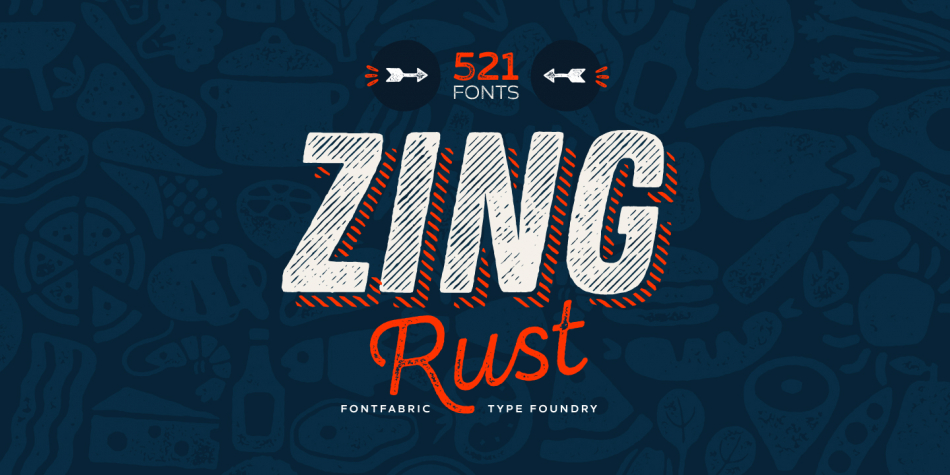
A fonte Zing Rust Font Family é uma família extensa de tipografia projetada com cuidado por Hamilton, disponível na categoria de Fontes para todos os seus projetos design. Especialmente indicada para criadores que buscam uma paleta vibrante e dinâmica, essa família oferece quatro subfamilias: Zing Rust, Zing Script Rust, Zing Sans Rust e Zing Goodies Rust. Zing Rust é o protagonista desta família, trazendo a essência vital e fresca dos ideais e das criações arrojadas de seus criadores. Zing Script Rust e Zing Rust incluem recursos OpenType com alternativas contextualizadas para oferecer uma ampla gama de personalização. A fonte Zing Rust é um ícone da família, destacando-se pelo seu design moderno e alegre, perfeito para aplicações que exigem um toque vibrante e ousado. Para projetos que buscam uma abordagem mais elaborada, as subfamilias de Zing Script Rust e Zing Sans Rust oferecem recursos adicionalmente únicos, garantindo um portfolio de design extremamente variável. Zing Goodies Rust serve como o complemento ideal para a família principal, adicionando nuances sutis e diversidade que não só enriquecem as soluções visuais da família, mas também proporcionam uma variedade impressionante de opções, garantindo que você tenha tudo o que precisa em um só lugar. Este é o ponto culminante da arquitetura do Zing Rust Font Family, com sua combinação perfeita de design alegre e funcionalidade abrangente, oferecendo uma solução completa para qualquer projeto de design visual.